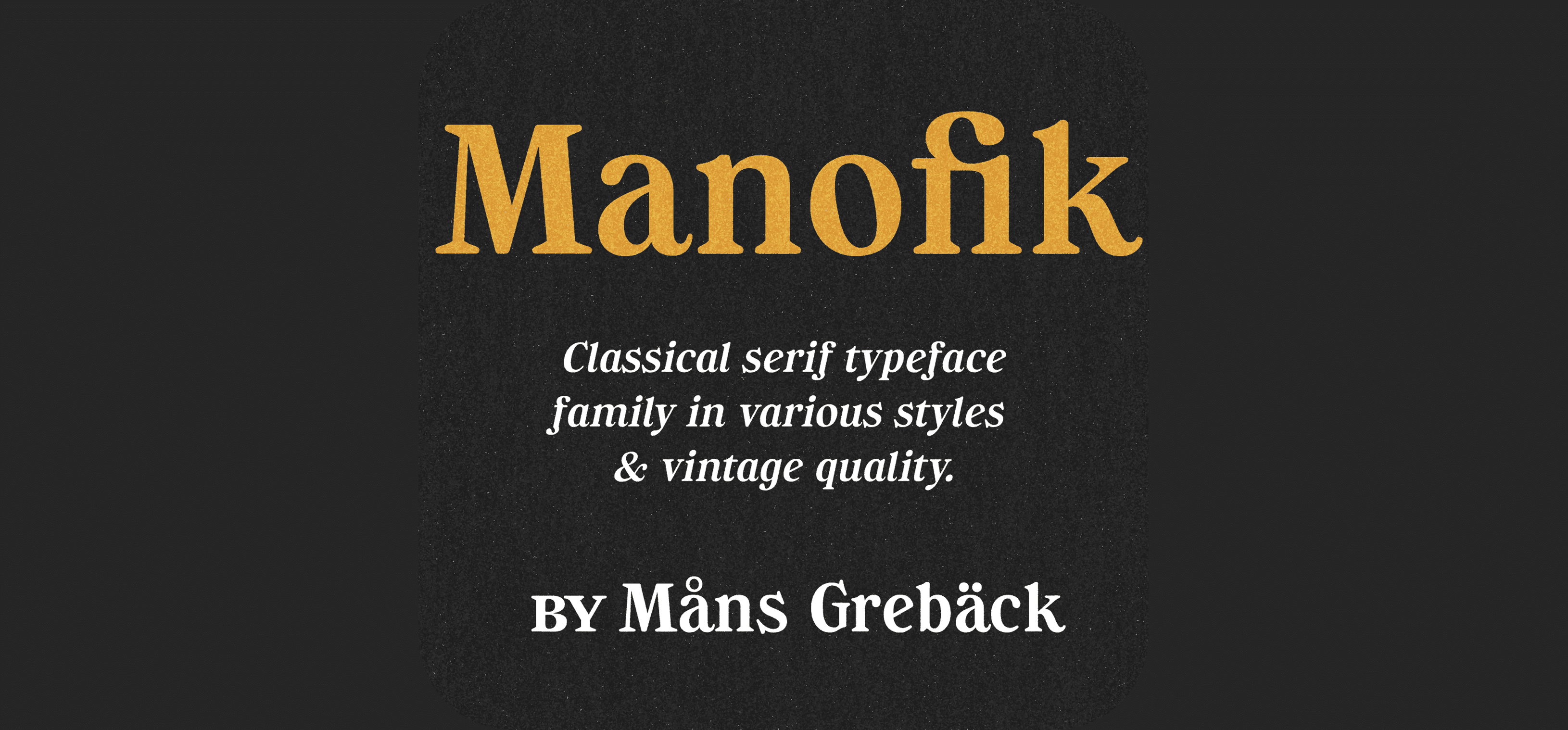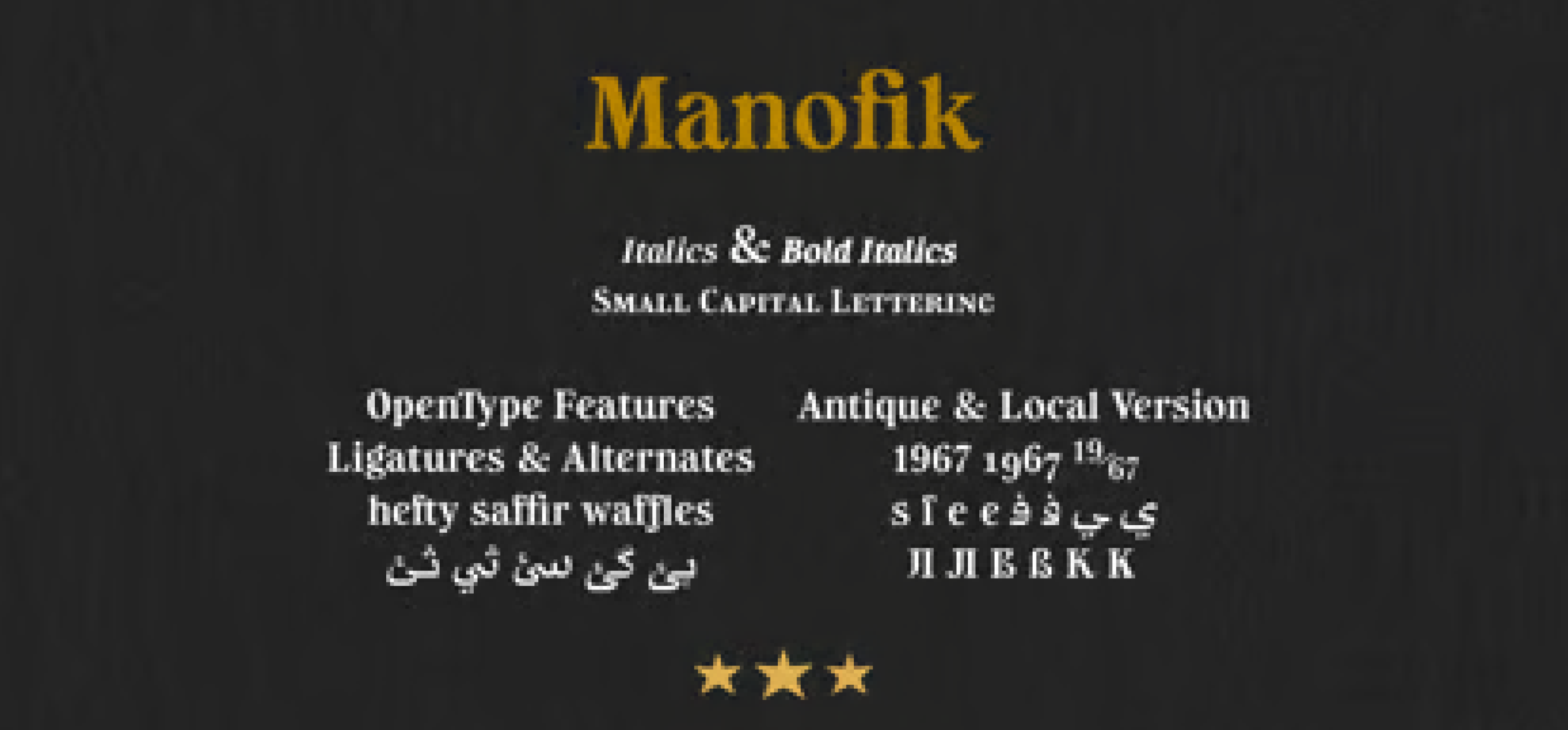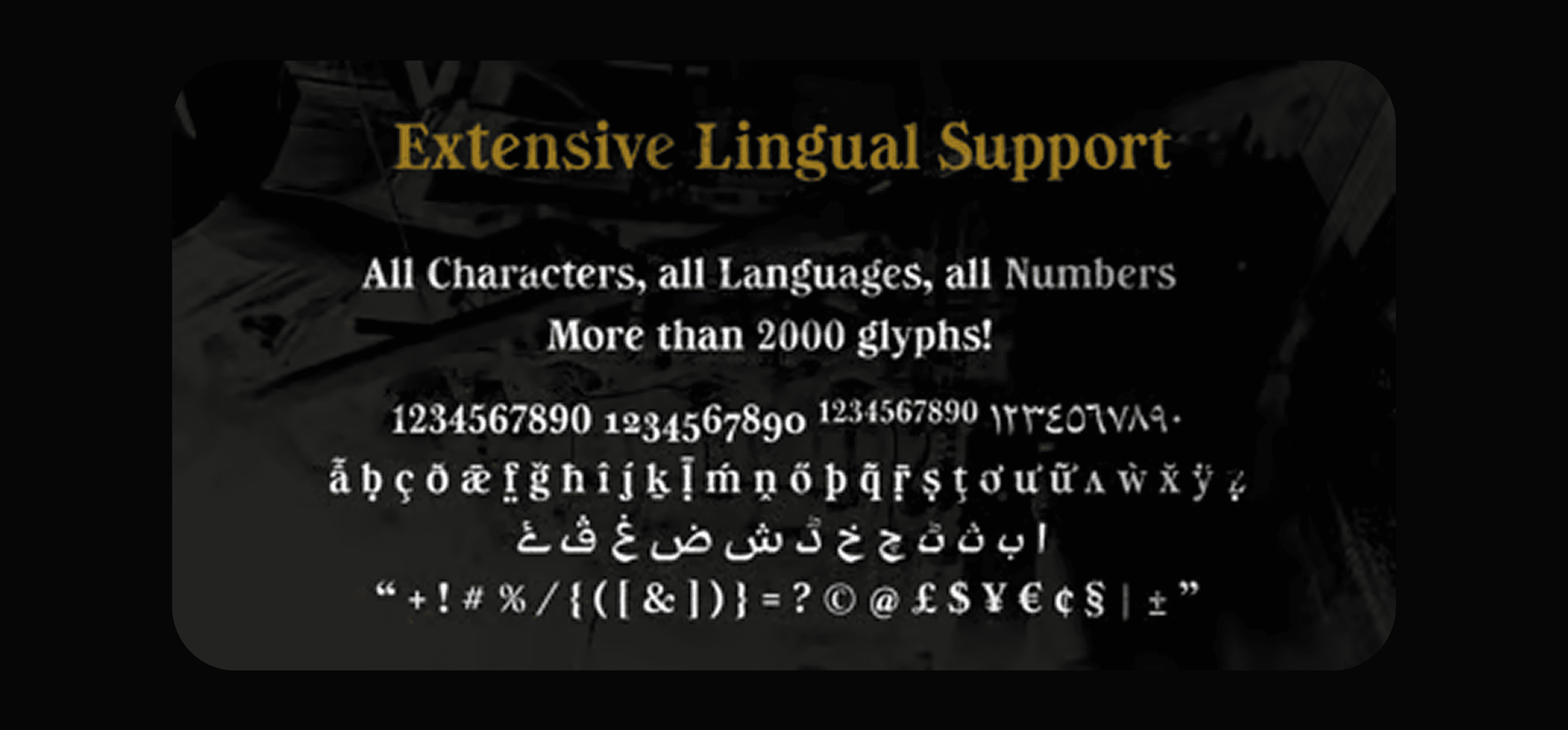
مانوفيك – Manofik هو خط سيرف تقليدي (كلاسيكي) يتميّز بأشكاله الدائرية والرجعية المريحة، وسُمكه المتوازن وقاعدته المستقرة.
يُعد منوفيك خطًا تقليديًا سهل القراءة، ويضفي لمسة من الأصالة على أي مشروع.
يمكن استخدامه في تصميم شعار لمطعم برغر، أو عنوان منتج، أو حتى في النصوص الطويلة التي تحتاج إلى لمسة شخصية مميزة.